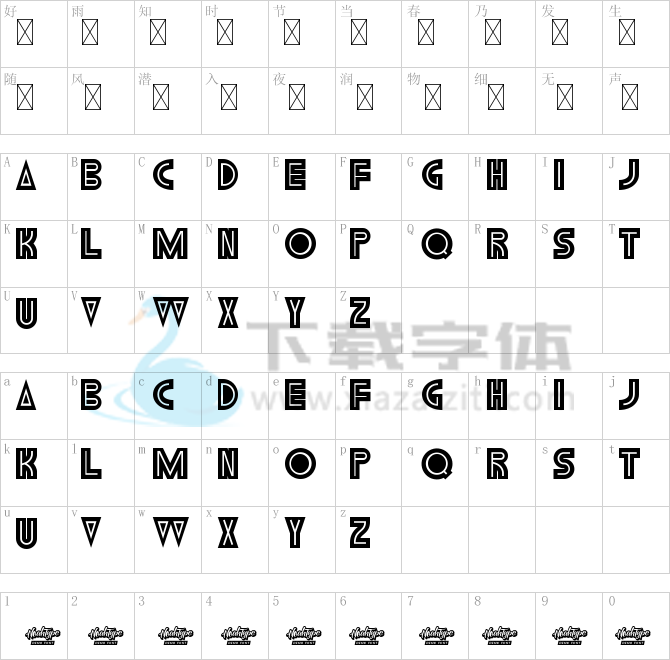
Aliver Aron Demo.ttf字体下载,这款字体结构工整、笔画清晰,兼顾美观与易读性,适用于标题、正文、海报、包装、LOGO 等多种场景。字形优雅稳定,风格百搭耐看,适配日常排版与创意设计,让文字呈现更舒适、更具质感。Aliver Aron Demo.ttf字体下载一笔一画,皆是细节,以均衡的比例、流畅的线条打造舒适视觉体验,字形端正大气,风格简约现代。无论是商业设计、品牌宣传还是日常排版,都能轻松驾驭,让文字更有格调与力量。Aliver Aron Demo.ttf字体下载字体下载。
Aliver Aron Demo.ttf图片展示
• 字体名称:Aliver Aron Demo
• 字体全名:Aliver Aron Demo
Aliver Aron Demo.ttf映射图